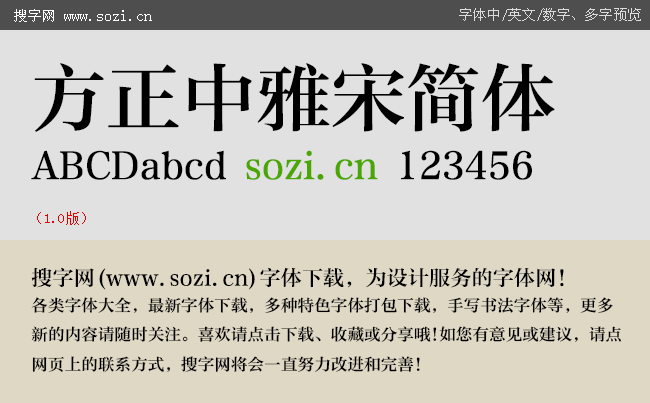
方正中雅宋簡體(FZZYSJW)
搜字網(wǎng)提供一款方正中雅宋簡體中文字體下載,方正中雅宋簡體是一款字形清秀的中文字體,該字體端正大方,粗細(xì)適中,結(jié)構(gòu)清晰,效果出眾,常用于產(chǎn)品設(shè)計(jì)、包裝印刷、報(bào)刊雜志、正文標(biāo)題、繪畫創(chuàng)作等廣告設(shè)計(jì)場合使用。